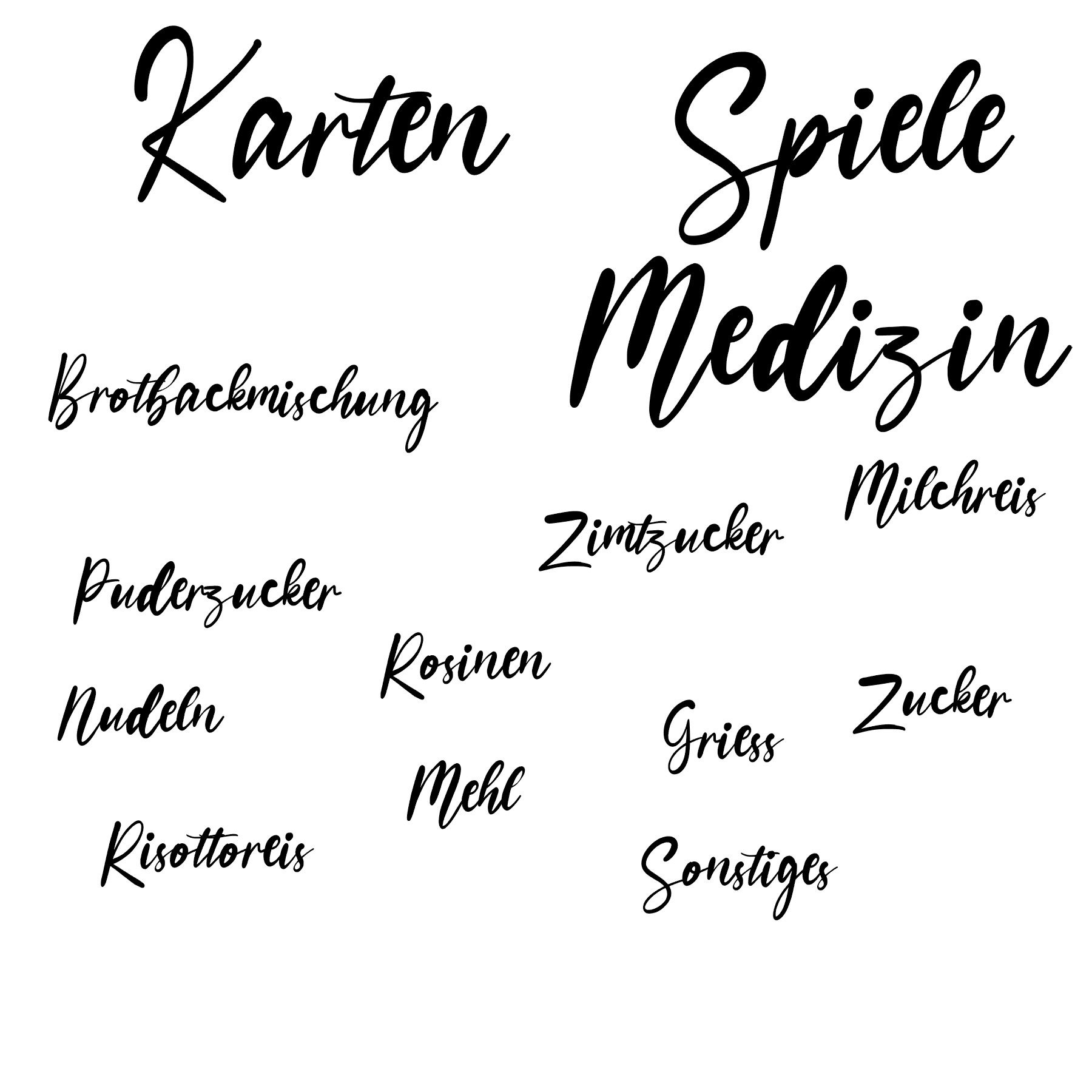
Wunderschönen kostenlosen Handwriting-Font wiederfinden
Diese Frage geht an die Schriftdetektive unter euch (bin erst heute auf dieses Forum gestoßen und begeistert, dass es das gibt):
Ich habe vor einiger Zeit Schriftzüge für meinen Vorrat geplottet und möchte diesen nun erweitern. Leider musste ich meinen PC aufgrund von einem Apple-Problem komplett löschen und konnte meine Schriftarten nicht mehr sichern. Ich versuche nun die besten Schriften anhand meiner alten Dateien (die die in der Cloud waren) wider herzustellen, allerdings habe ich die Schrift damals in Pfade konvertiert und verbunden, weshalb ich nicht mehr auf den Schrift-bearbeiten-Zustand komme.
So wie ich mich kenne ist es wahrscheinlich eine kostenlose Schriftart und ich habe den Buchstabenabstand so verändert, dass aus den Einzelnen Lettern durch Überlappen ein zusammenhängender Font entsteht.
Ich finde die Schrift wunderschön und würde mich freuen, wenn mir jemand hilft wenigstens meine beste Schriftart (diese) wider zu finden.
Hallo knobldobl, willkommen im Forum,
wenn Du die Vektoren eh schon hast, schnibbel doch mal die verbundenen Vektoren auseinander und stelle ein paar markante Buchstaben mit etwas Abstand auf eine Grundlinie und jage das durch Whatfontis. So würden das die Kolleg*innen das hier im Zweifel auch (nur) machen.
Dieser Art Schriften sind/waren extrem angesagt in der letzten Zeit. Creative Market scheint mir nur aus solchen zu bestehen 🙂
danke für die schnelle Antwort. Ich habe den Tipp schonmal in einem früheren Thema gelesen und bereits mit den voll-freigestellten Großbuchstaben versucht. Leider sind die zusammenhängenden Buchstaben nicht mehr auseinander zu bekommen (habe das Programm Silhouette Studio genutzt und da geht keine Rückverfolgung mehr) und der Versuch ein paar von ihnen zu lösen (siehe Anhang) ging auch schief. Ich hab das Bild mal noch als SVG angehängt, vielleicht bin ich auch einfach nur unfähig 😂
Leider muss die Schriftart wirklich identisch sein, da ich damals Schablonen erstellt habe und die Schrift in Glas geätzt habe. Um ein wirklich einheitliches Bild zu erhalten geht also nur eine Schriftart, die wirklich passt und nicht nur ähnlich ist 😒
Normalerweise nutze ich nur kostenlose Schriftarten und fontspace ist eine meiner meistgenutzten Seiten (bin mir aber nicht sicher ob ich dafür nicht das anderes verwendet habe)
Habe jetzt den ganzen Tag nach der dummen Schrift gesucht und bin echt verzweifelt :-(
🥳 ich hab sie gefunden
Ein hoch auf den Apple-Schlüsselbund, weil der kannte meinen (laut sofontsy-website gelöschten) Account noch und dann hab ich da alle Schriftarten noch durchgesucht und gefunden - der Name kommt mir bekannt vor und es ist exakt die Schriftart
Na Fontspace war doch ein guter Hinweis … bei Stichwort Calligraphy auf Seite 2
...wurde doch der sofontsy-Download weil die Fontspace-Demo hat ein zu lang gezogenes n und b :-)